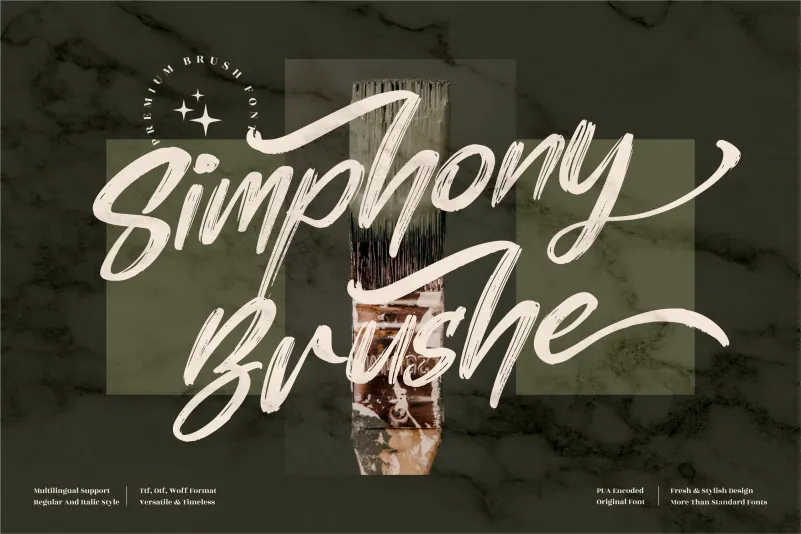
A Simphony Brushe Font é uma fonte feita à mão que oferece um toque autêntico para qualquer projeto. Conhecida por seu estilo elegante e sofisticado, essa fonte perfeita para aplicar em diversas áreas de design. A sua utilização irá enriquecer logos, marcas de projeto, designs de mobiliário, embalagens de produtos, taças, selos e até mesmo fotografias. Simphony Brushe é uma escolha atraente tanto para trabalhos diárias quanto para momentos especiais, desde convites até etiquetas. É um complemento perfeito para quem valoriza detalhes e deseja dar um toque pessoal em projetos de design. Seja qual seja o seu propósito de projeto, Simphony Brushe garantirá que sua mensagem ou arte se destaque com uma sensação única e delicada do mundo dos desenhos à mão livre.